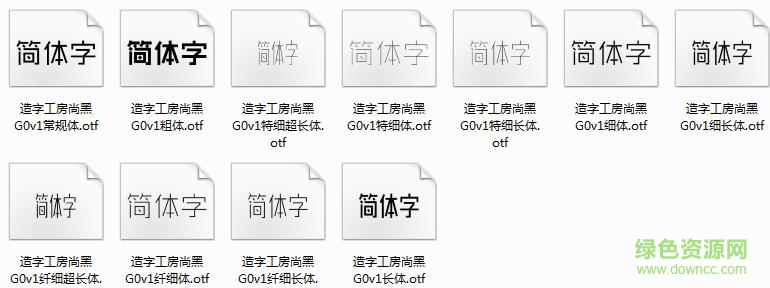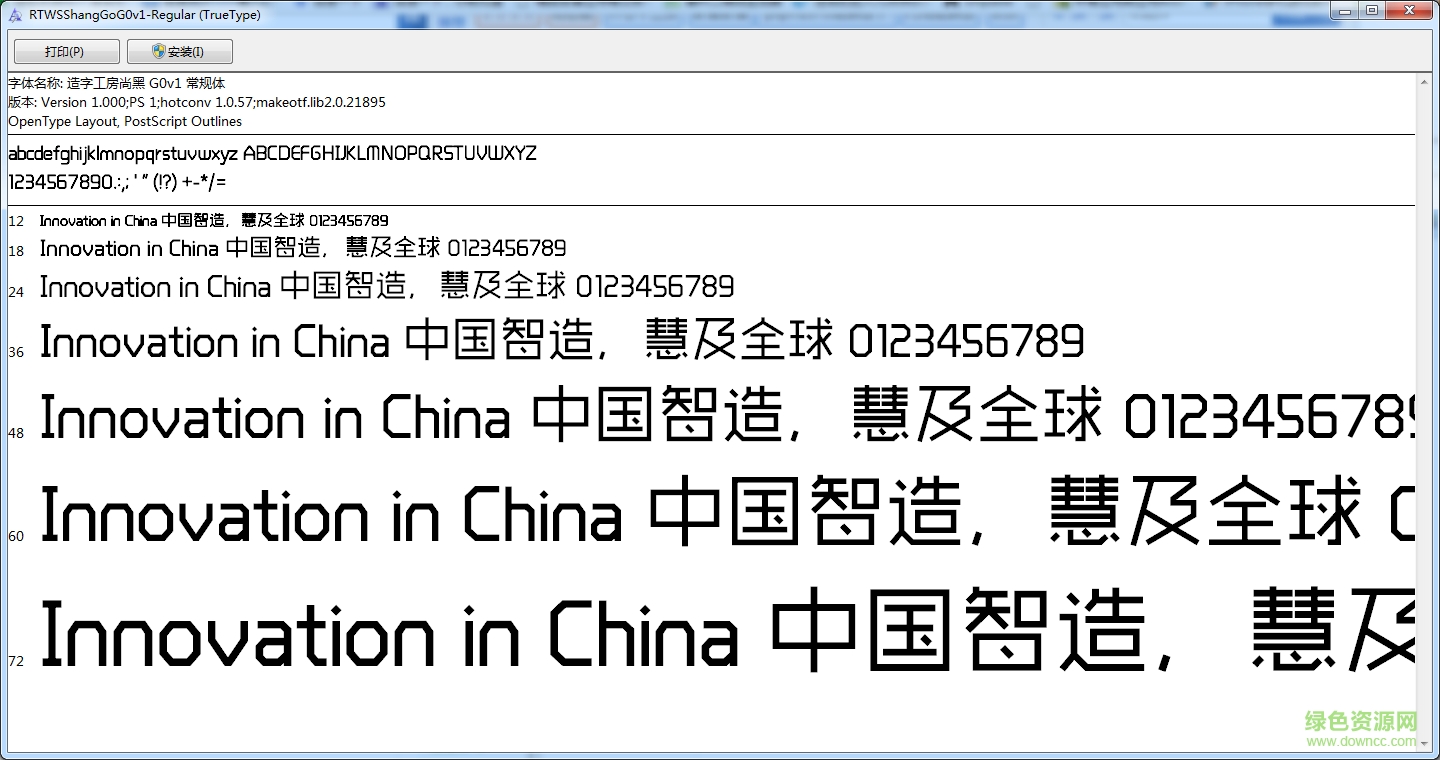
rtwsshanggog0v1字體合集包含了bold、regular、exlight、condensed、light等十一款造字工房尚黑g0v1字體,設(shè)計(jì)感強(qiáng),新穎實(shí)用,需要的朋友快下載收藏吧!
rtwsshanggog0v1字體特點(diǎn)
造字工房尚黑g0v1系列字體個(gè)性鮮明,字體造型規(guī)整,富于力度,打破傳統(tǒng)字體設(shè)計(jì)局限,有較強(qiáng)的視覺沖擊力,適用標(biāo)題與廣告以及機(jī)械科技等主題!
黑體字體介紹
沒有襯線的字體通常稱為黑體,這時(shí)這個(gè)詞的范疇和無襯線字體(Sans-serif)是類似的。所以在中文字體中常用“黑體”,在西文中常用“無襯線體”的稱呼。